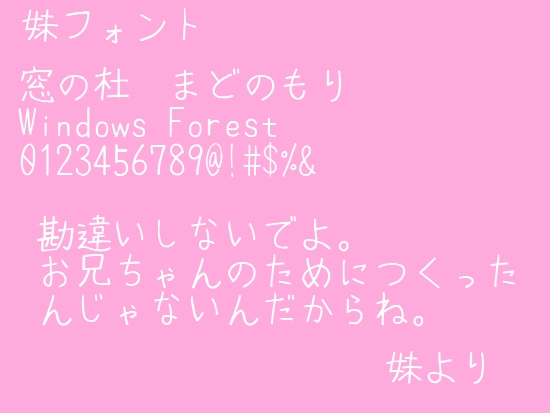
一种免费的等宽 TrueType 字体,可再现柔和的手写字符。据作者介绍,该字体是按照像妹妹一样努力认真写字的女孩形象创作的,看起来就像是高年级小学或初中女生在笔记本上精心书写的。以手写风格完成。它包含几乎所有半角和全角字母数字字符、平假名、半角和全角片假名、JIS 1 级和 2 级汉字、希腊字母、俄语字母和扩展汉字,因此可用于广泛的用途。目的范围。它可以免费用于个人和商业目的,并且只要免费分发就允许重新分发。
“姐妹字体 SistersFB”是一款书写很新颖的字体,字体大方,适合各种设计作品使用!欢迎下载!